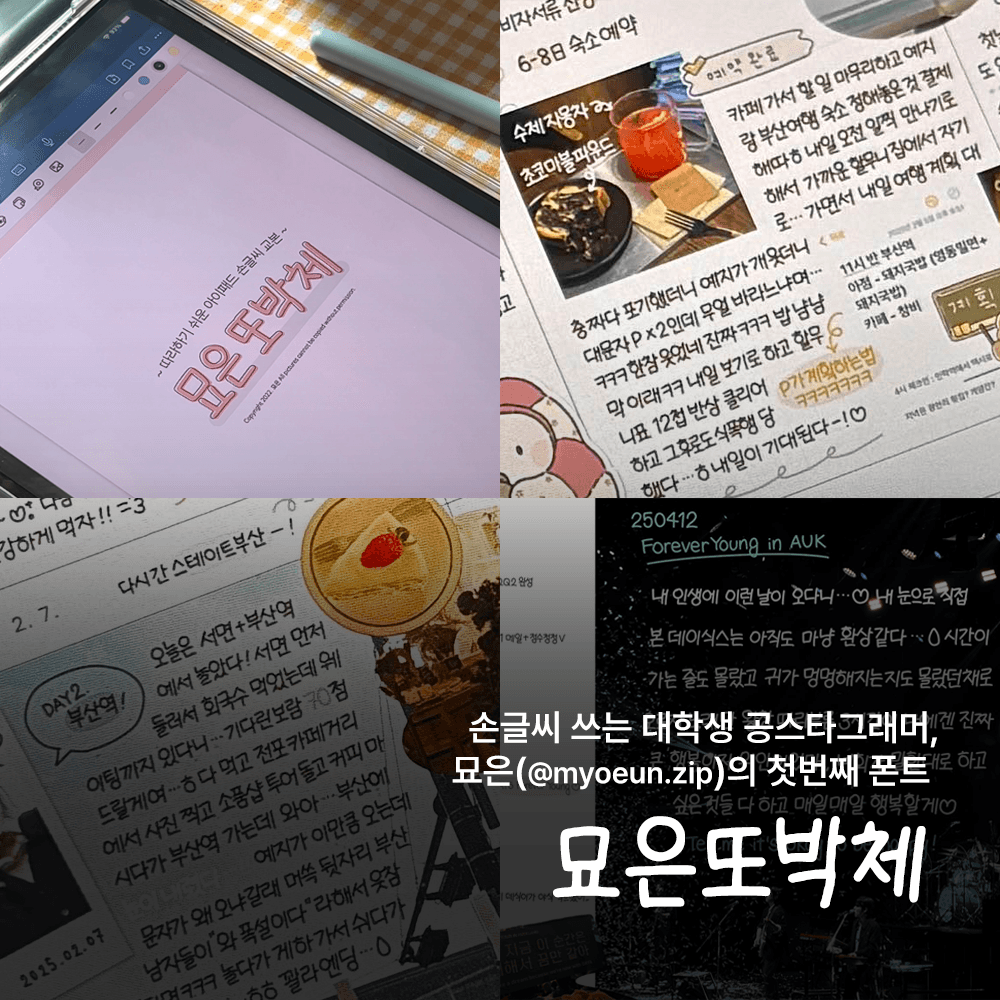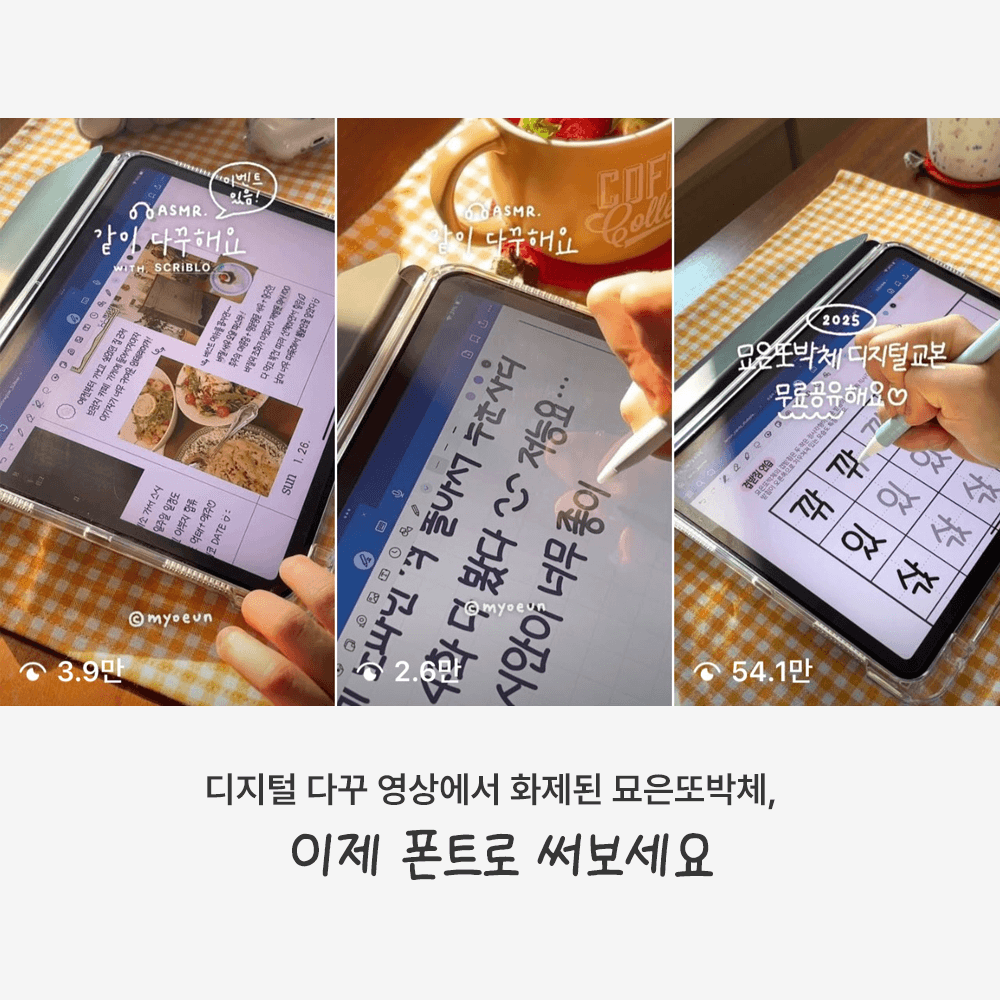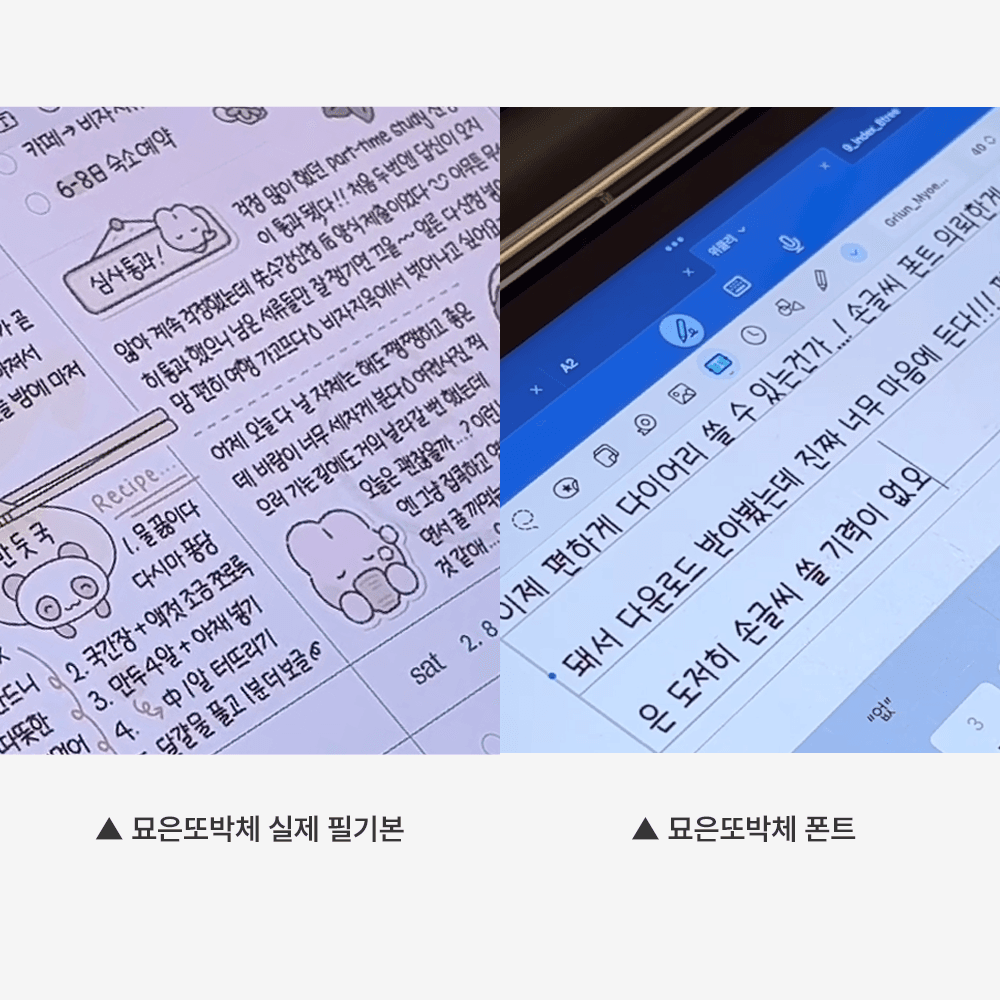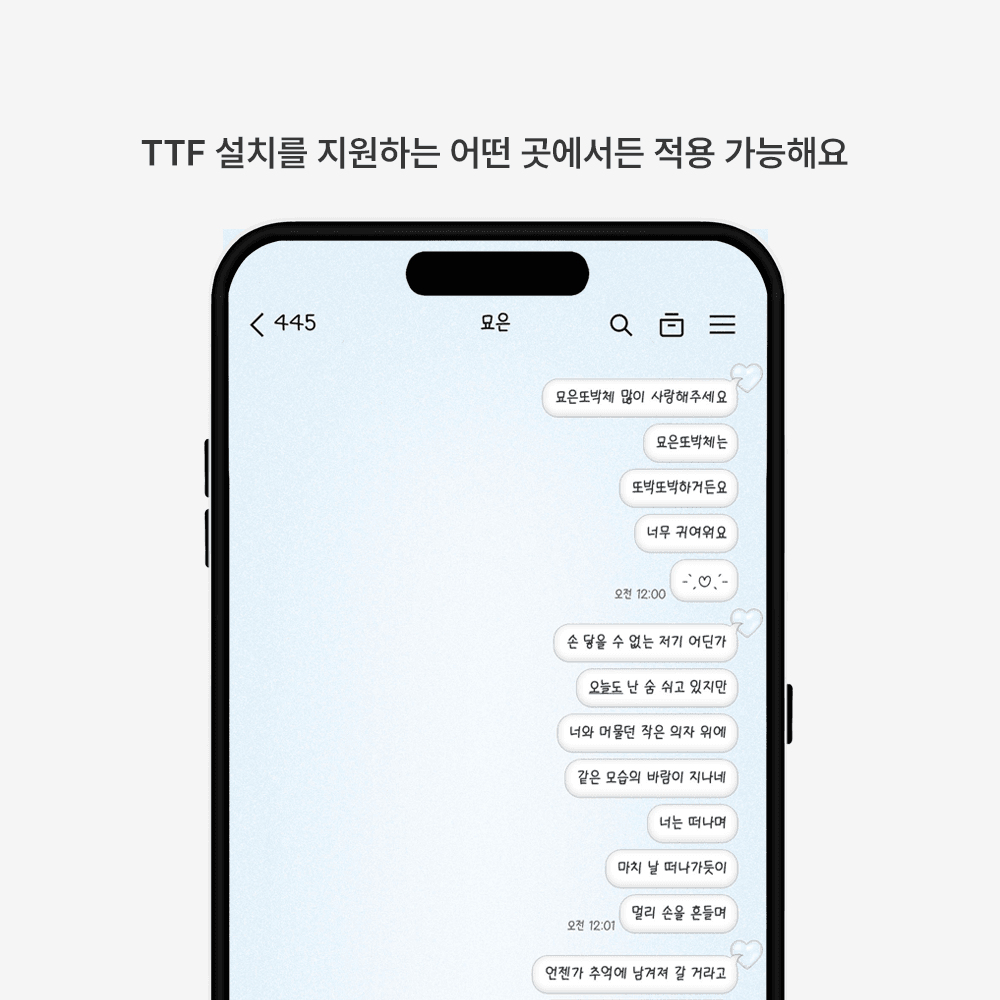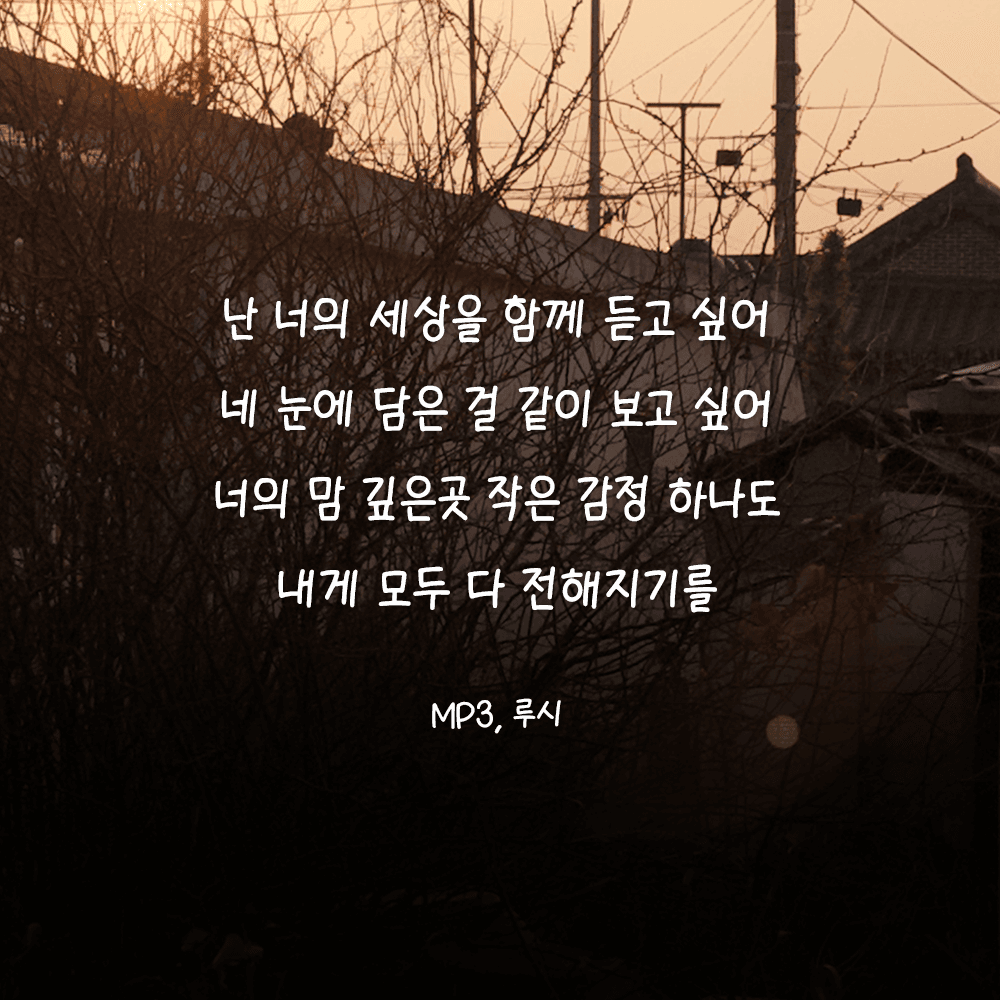
그리운 묘은또박체
Griun Myoeunddobak
그리운 묘은또박체 소개
그리운 묘은또박체(Griun Myoeunddobak)는 정갈하면서도 귀여운 느낌의 손글씨 폰트입니다. 또박또박 눌러쓴 듯한 매력이 있어 ‘묘은또박체’라는 이름을 붙이게 되었어요. 소셜미디어에서 바이럴된 저의 손글씨 영상을 바탕으로, 그 글씨체를 그대로 폰트에 담아보았습니다. 꾹꾹 눌러쓴 손글씨가 여러분의 진심을 전하는 데 조금이나마 도움이 되었으면 하는 마음으로 만들었답니다. 묘은또박체는 노트 필기부터 굿즈 제작까지, 어디에나 잘 어울리는 누구나 편하게 쓸 수 있는 폰트입니다.묘은또박체와 함께, 또박또박 당신의 이야기를 써 내려가 보세요. --- [관리자 공지사항] --- 업데이트 히스토리 ver.1.1 '꿔' 오탈자 이슈로 파일 교체 (2026-06) 페이지 새로고침 후 다운로드 바랍니다. 이용에 불편을 드려 죄송합니다. 🙇